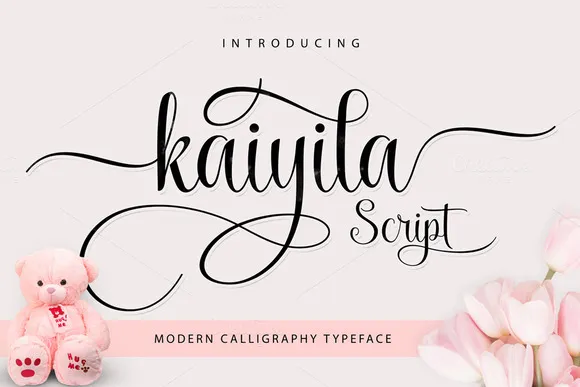
Kaiyila Script Font – Download Grátis
Kaiyila Script é uma nova fonte script que traz à tona estilo moderno e fresco, combinado com detalhes únicos que lembram a arte handmade de escritura cálida. Esta fonte não apenas adiciona um toque especial às cartas de cumprimentos e convites, mas também se destaca em materiais de marca, business cards, cartazes e até mesmo naquelas incríveis frases que você deseja destacar. Com seus personagens decorativos e linha de base dançante, Kaiyila Script torna-se um recurso indispensável para designers que desejam dar à sua identidade visual um toque único e sofisticado. É perfeito para quando você quer deixar seu design impressionar o público com elegância e criatividade.